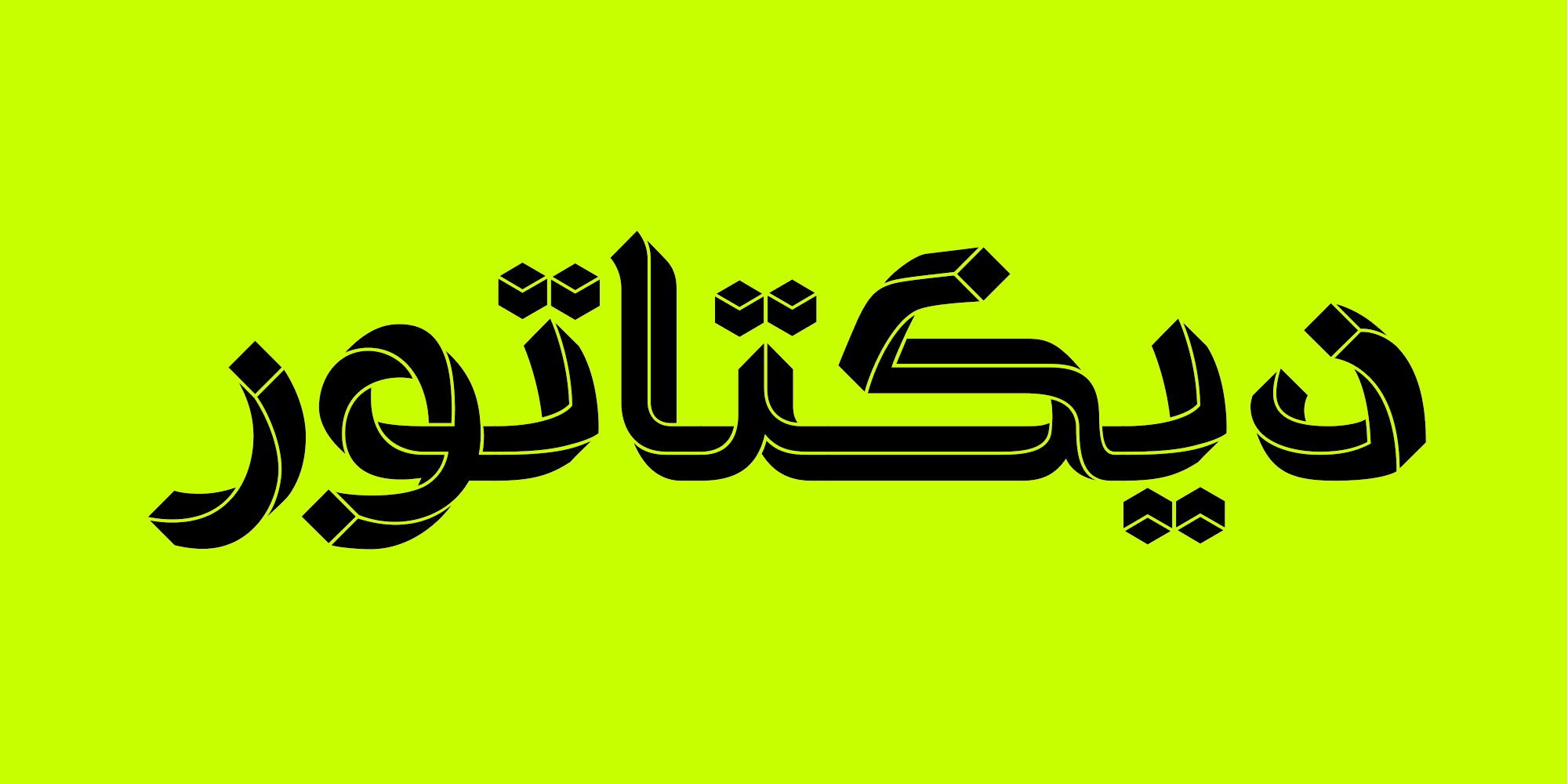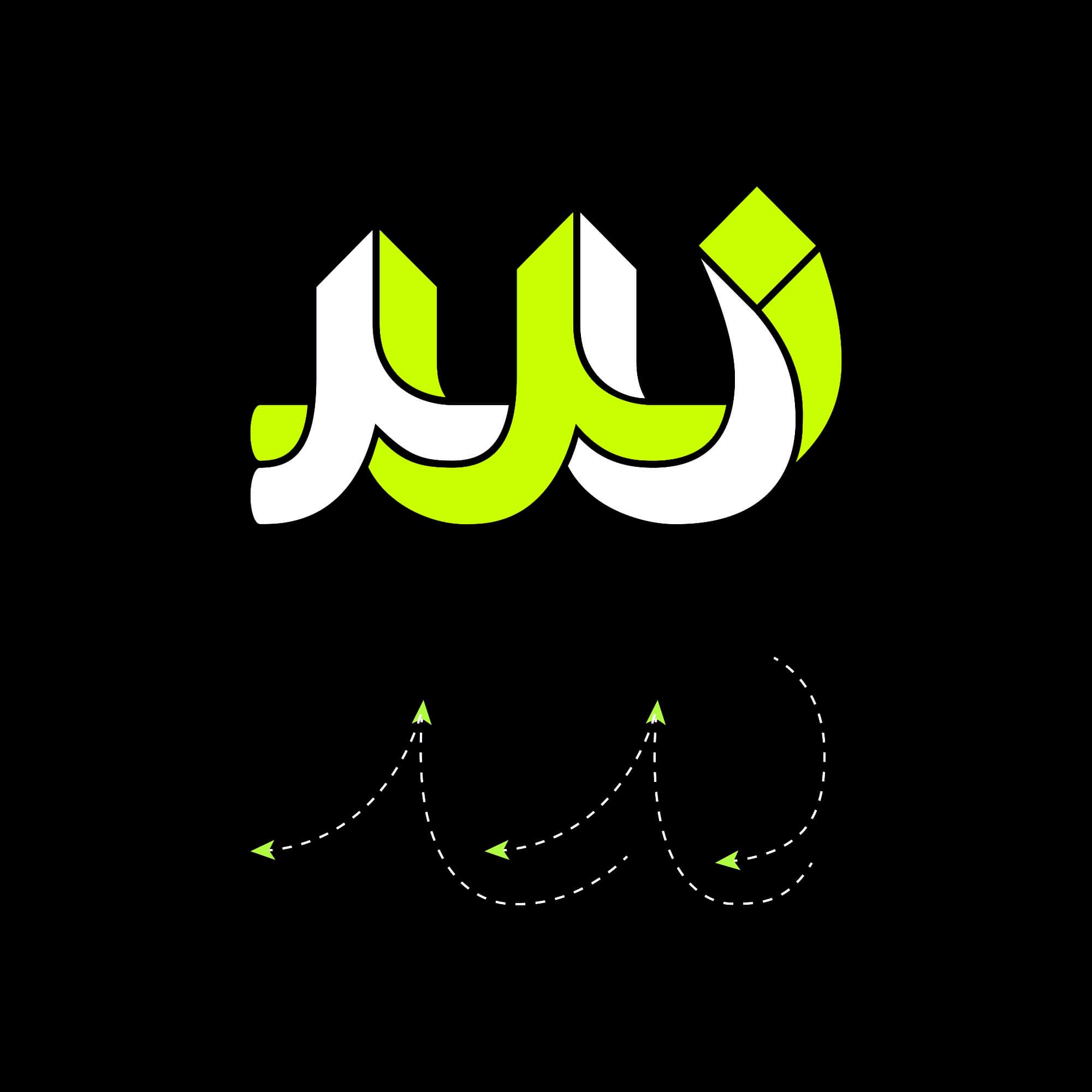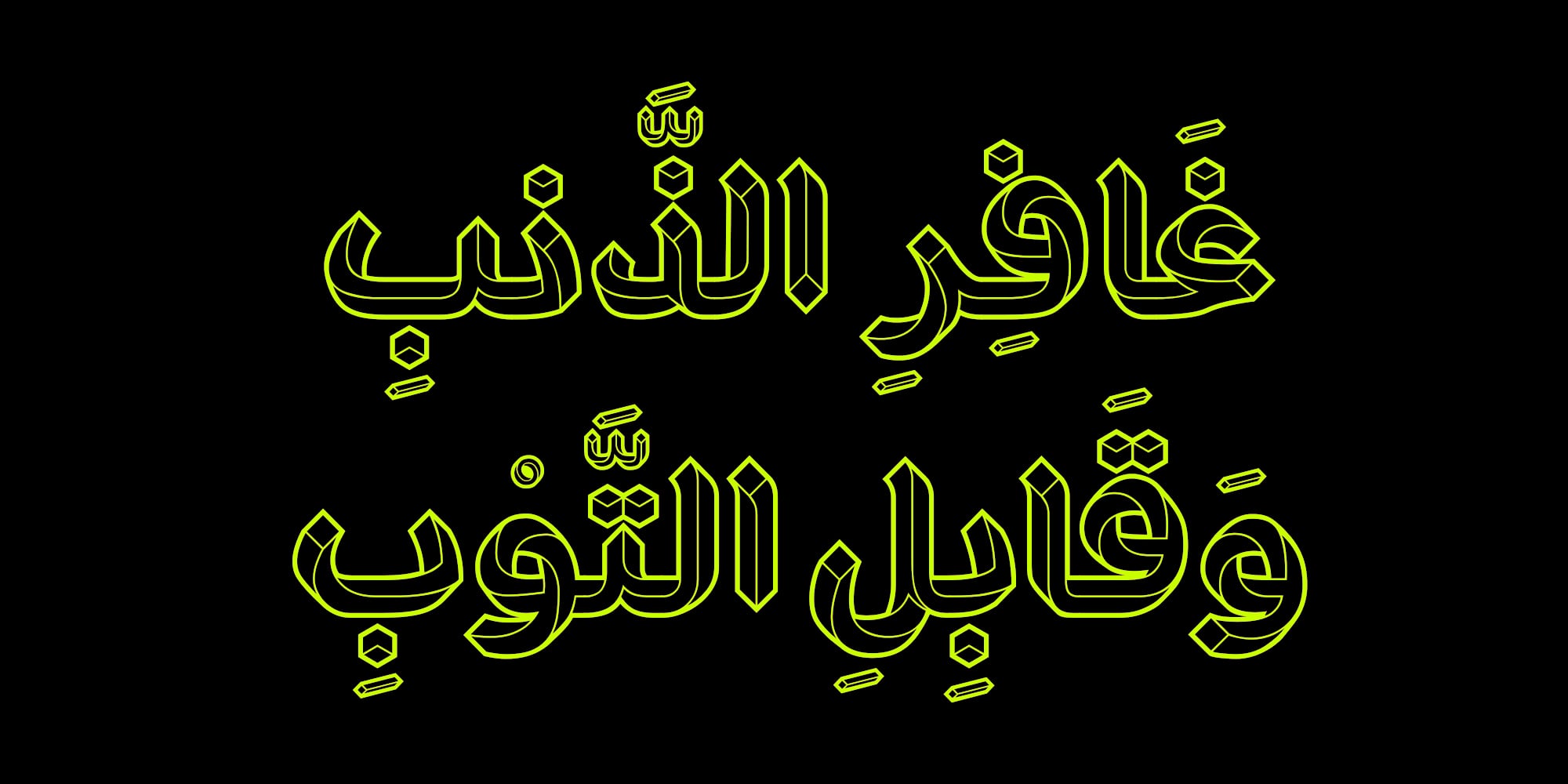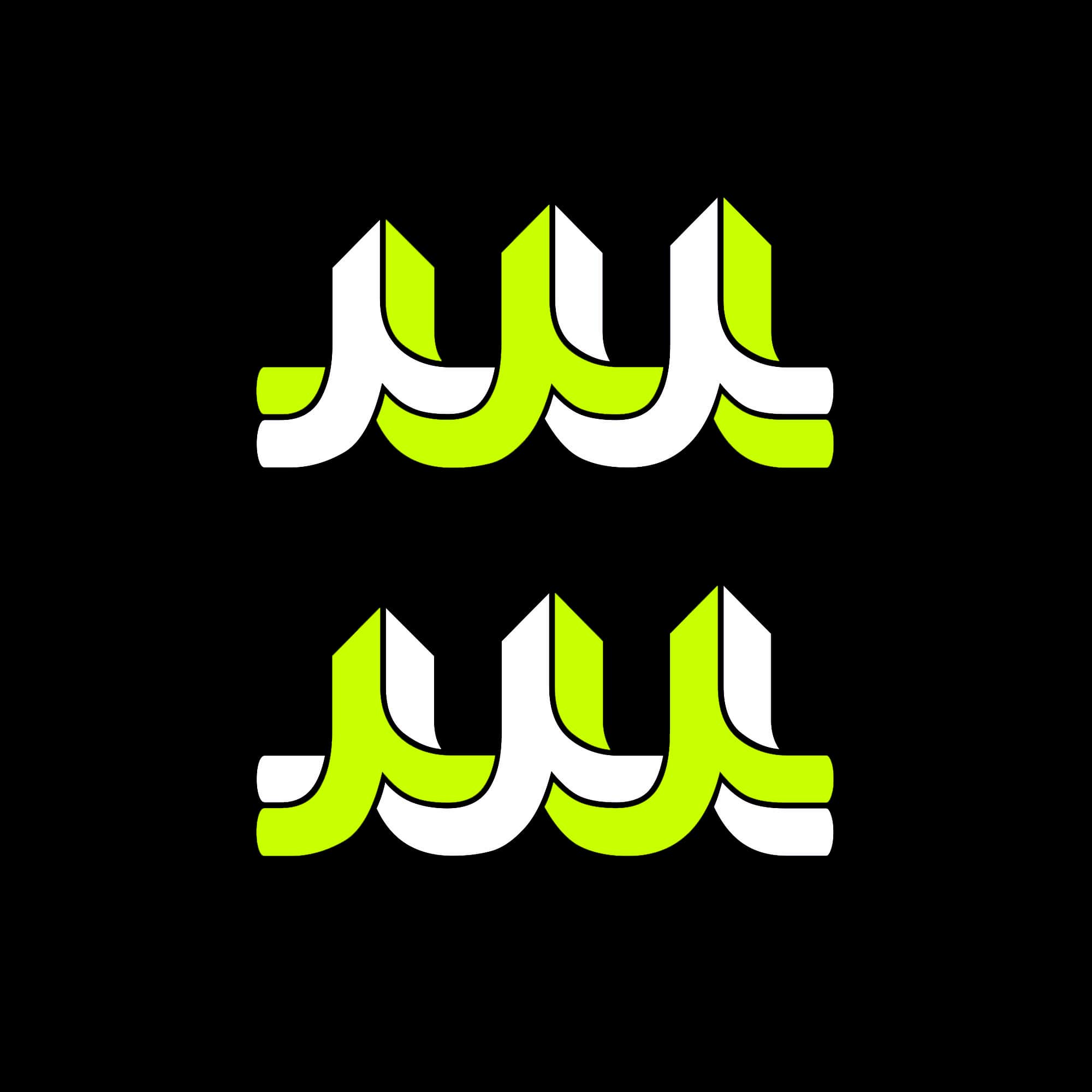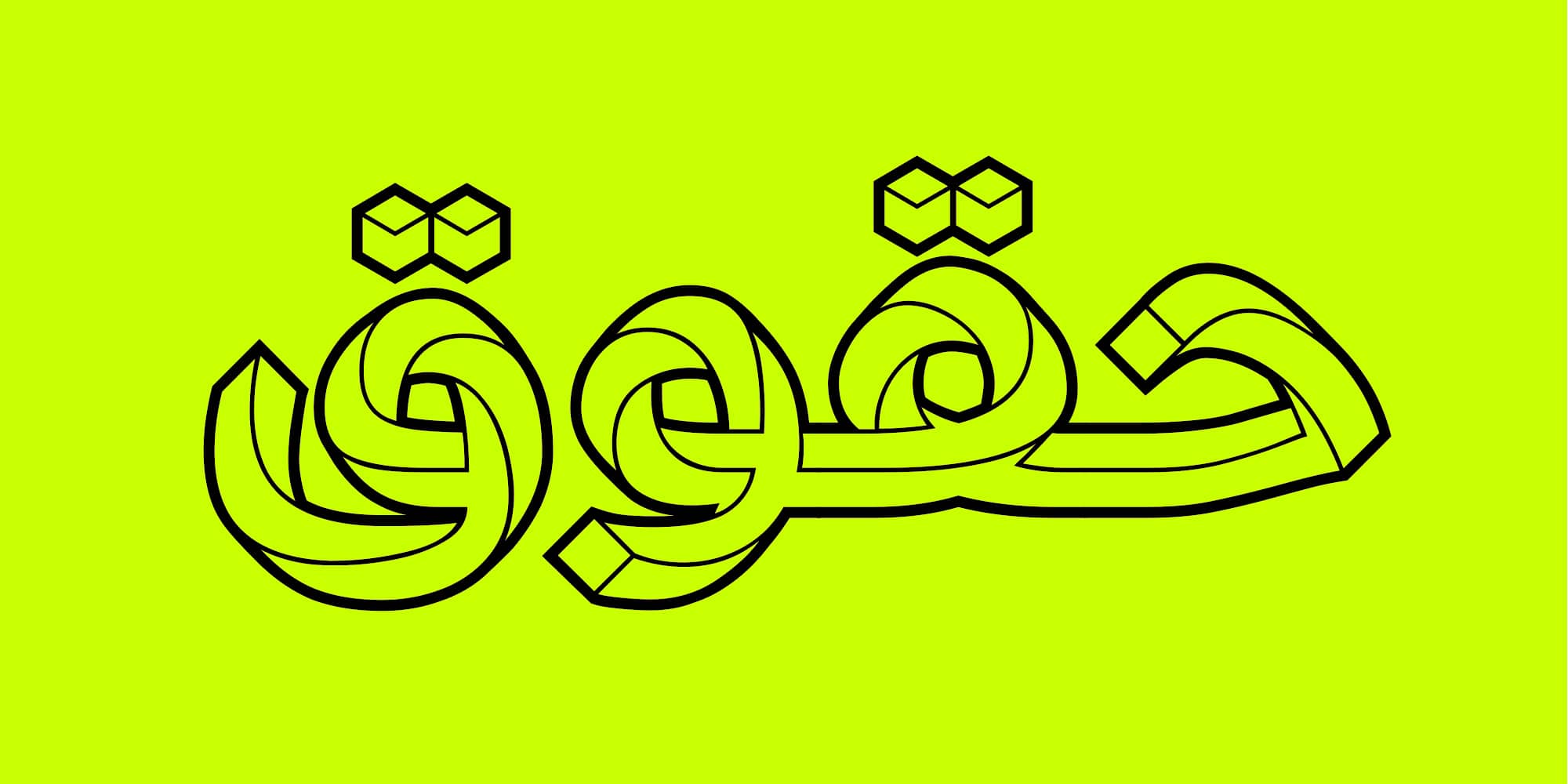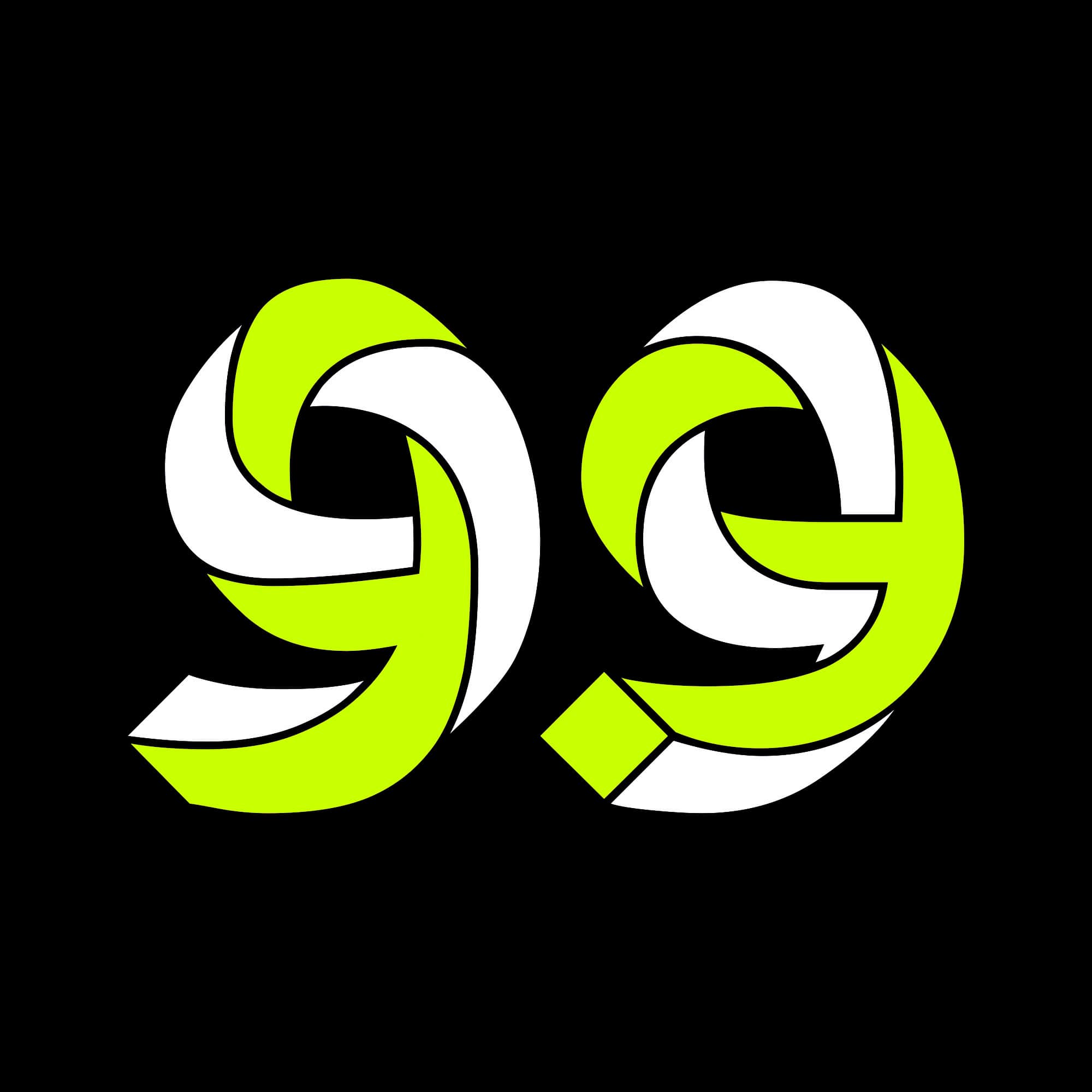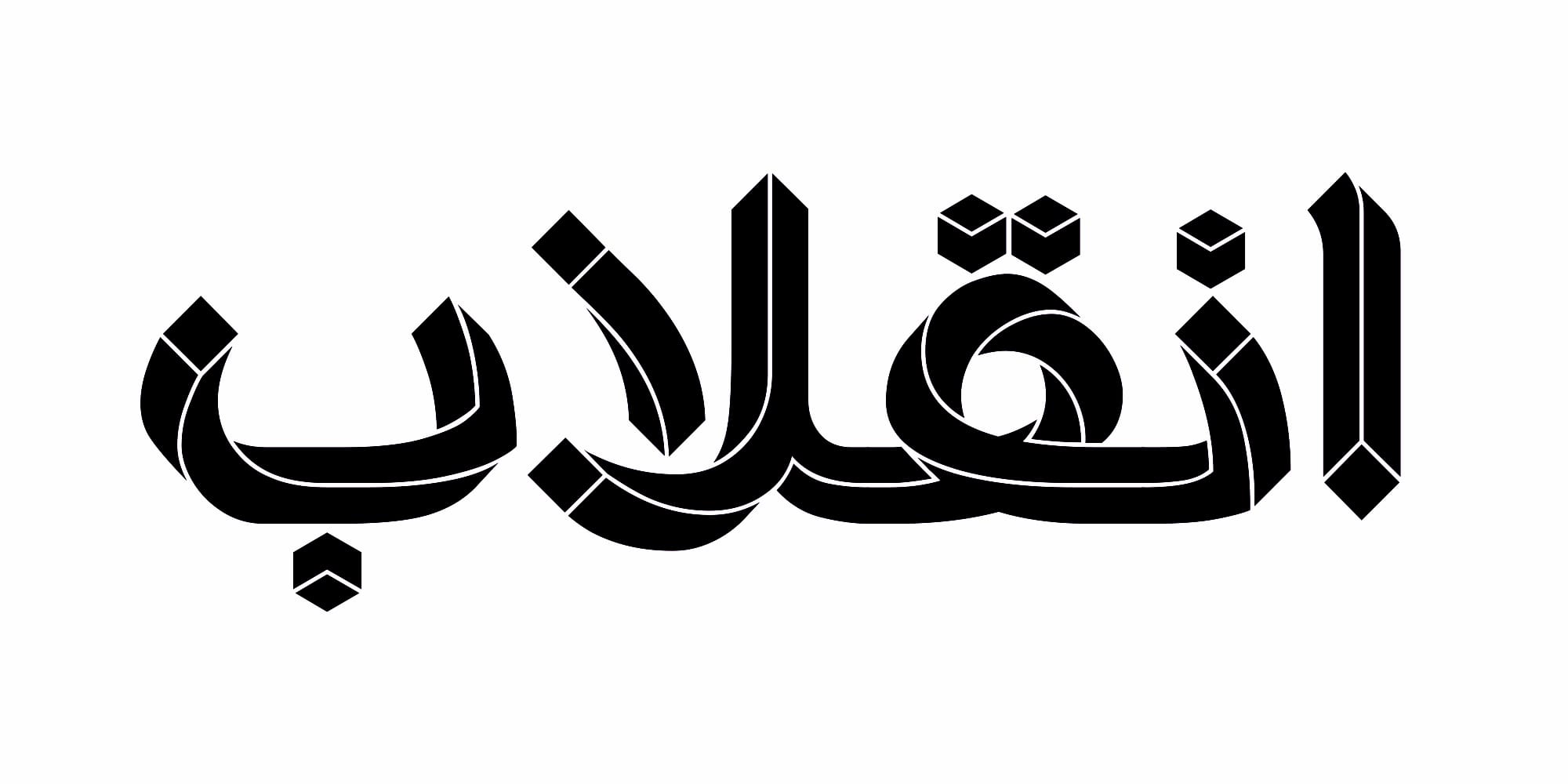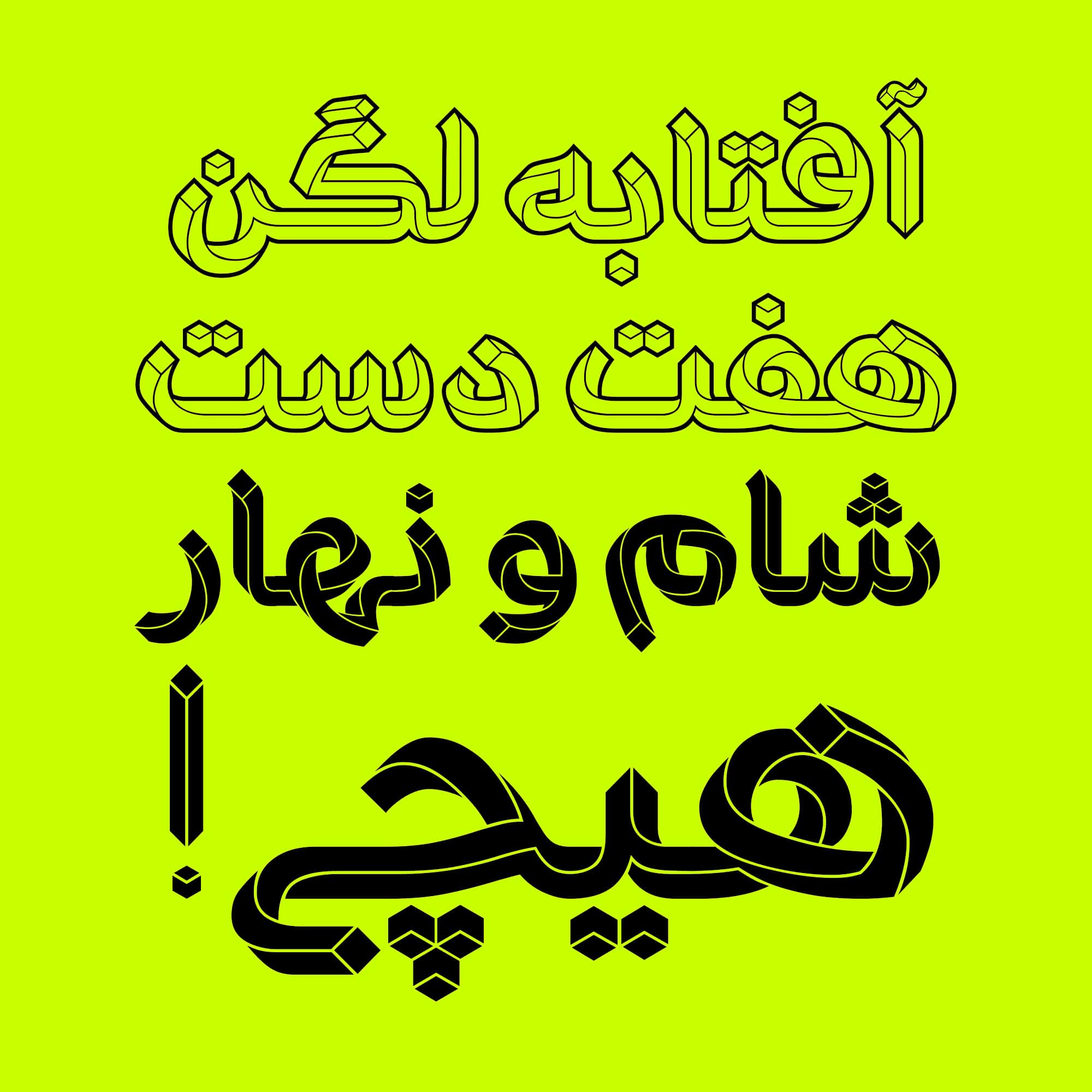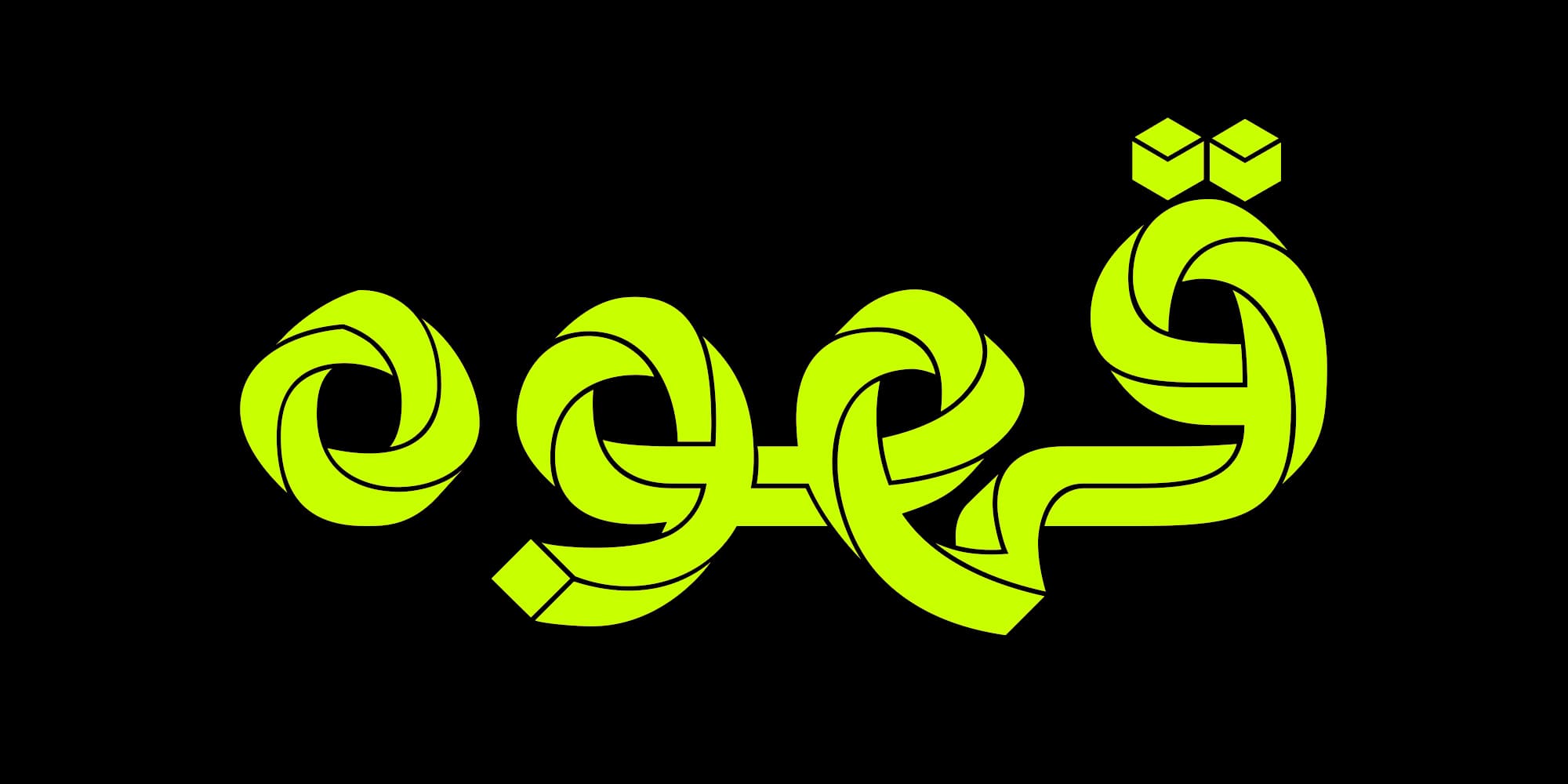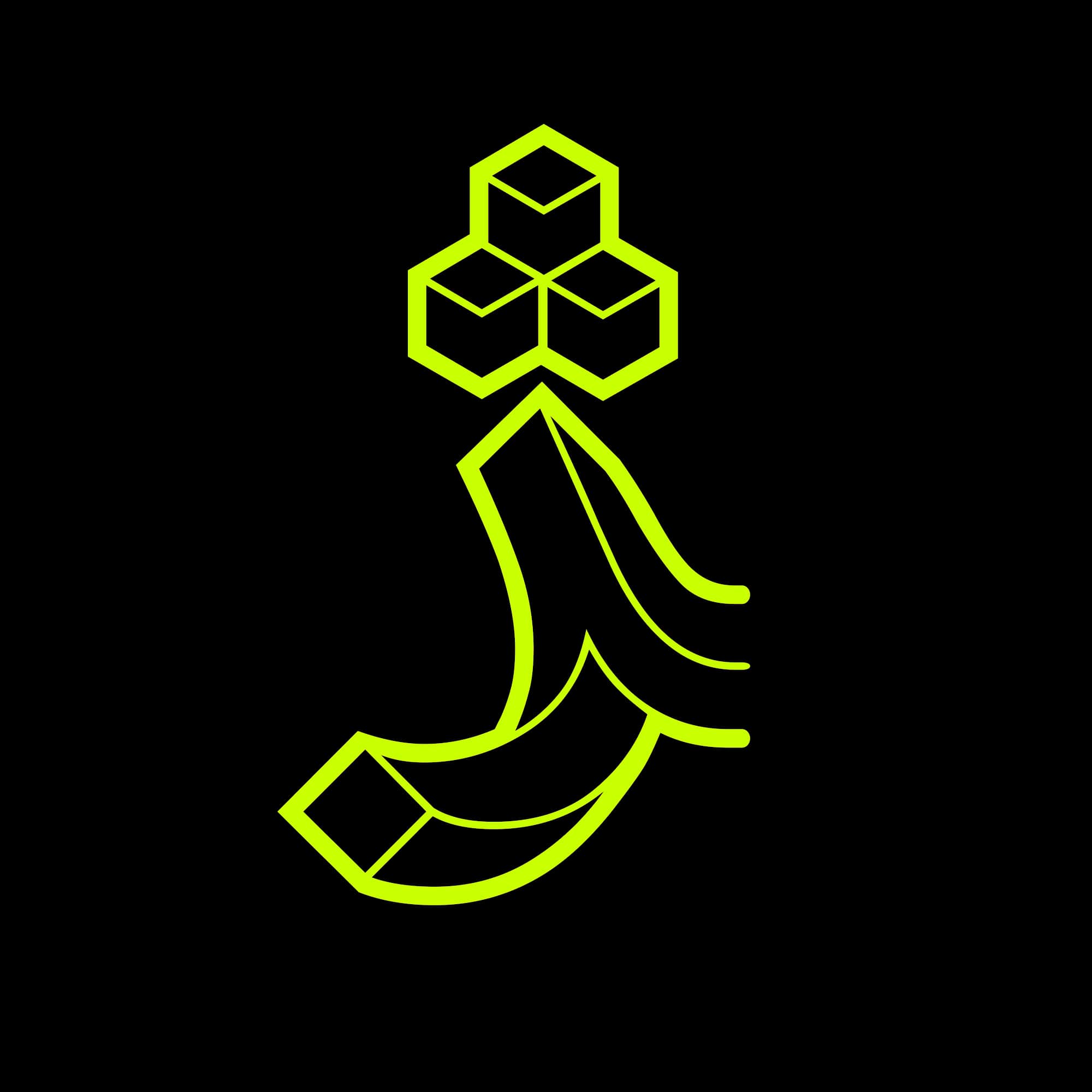
ایده ساخت فونت پارادوکس به دلیل علاقه شخصی من به آثار موریس اشر، از سال ۹۳ شروع شد. با جستجو و آزمون و خطا، به طراحی پرداختم و در این مسیر، تعدادی فونت لاتین هم پیدا کردم که همین کار را انجام داده بودند. اما حروف فارسی بسیار پیچیده از لاتین بود، الگوهای خط لاتین پاسخگو نبود و من مجبور بودم وقت زیادی را برای حل چالشها صرف کنم.
در سال ۹۸، با تمرکز جدیتر به طراحی فونت پرداختم و نهایتاً تا پایان همان سال، طراحی و اجرای نرمافزاری آن تقریباً تمام شد. در سال ۱۴۰۱، با راهنمایی دقیق و موثر دوست خوبم، امین عابدی (برای کد نویسی) نهایتاً فونت پارادوکس آماده انتشار شد.
فونت پارادوکس یک نمونه جذاب و خلاق در زمینهٔ طراحی فونت است. این فونت با ترکیبی از خطوط خمیده و تیز، یک هماهنگی منحصر به فرد ایجاد میکند که به تصویر ظرافت و پیچیدگی میانجامد. در این فونت، از خطای دید به عنوان یک عنصر طراحی استفاده شده است تا حروف با یکدیگر هماهنگی زیبایی داشته باشند. با تعدیل دقیق خطای دید، حروف در کلمات به طور هنرمندانهای ترکیب شدهاند و این ویژگی زیبایی و تنوع به طراحی متون با فونت پارادوکس افزوده است.
نمونه حروف جایگزین در فونت پارادوکس